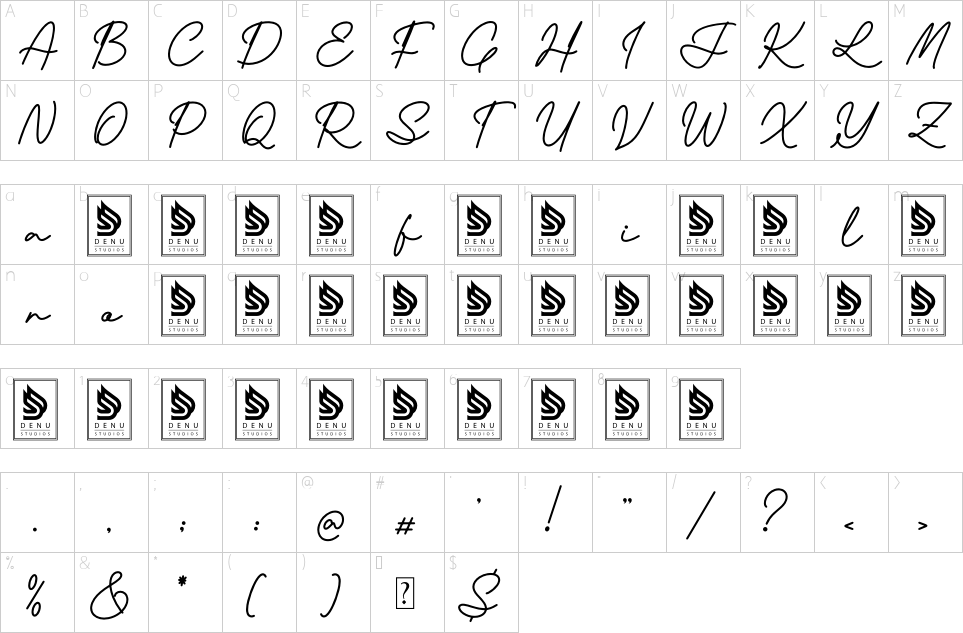
A Pafilona é uma fonte lúdica e deslumbrante, perfeita para personalizar qualquer projeto. Desenhada pelo Gracetypestudio, esta fonte apresenta linhas elegantes e nuances levemente irregulares que garantem um toque agradavelmente único e moderno. Com seu design cuidadosamente elaborado, a Pafilona é ideal para textos digitais e impressos, sejam eles legais, resumos ou até mesmo design gráfico. Disponível tanto para Windows quanto para Mac, a Pafilona é uma escolha excelente para quem procura um recurso gráfico atencioso e versátil. Com apenas 370 downloads, a Pafilona é uma fonte gratuita que merece ser explorada e experimentada, garantindo que seu próximo projeto seja ainda mais atraente e personalizado.